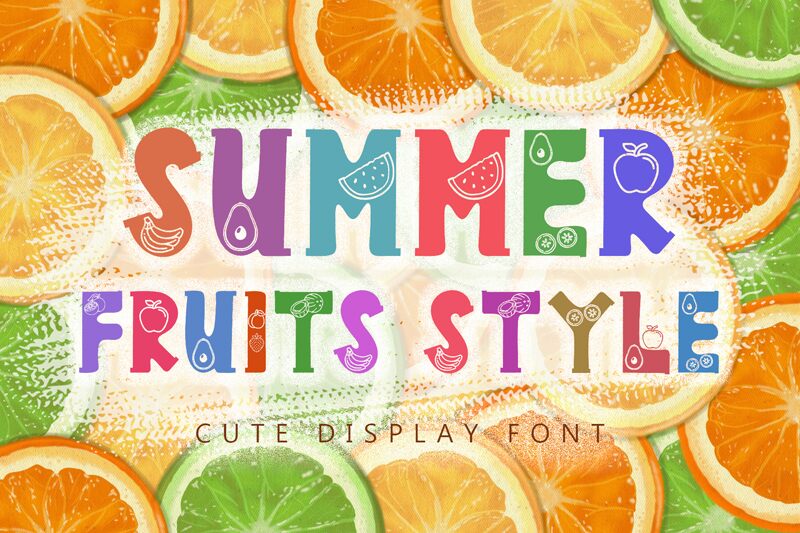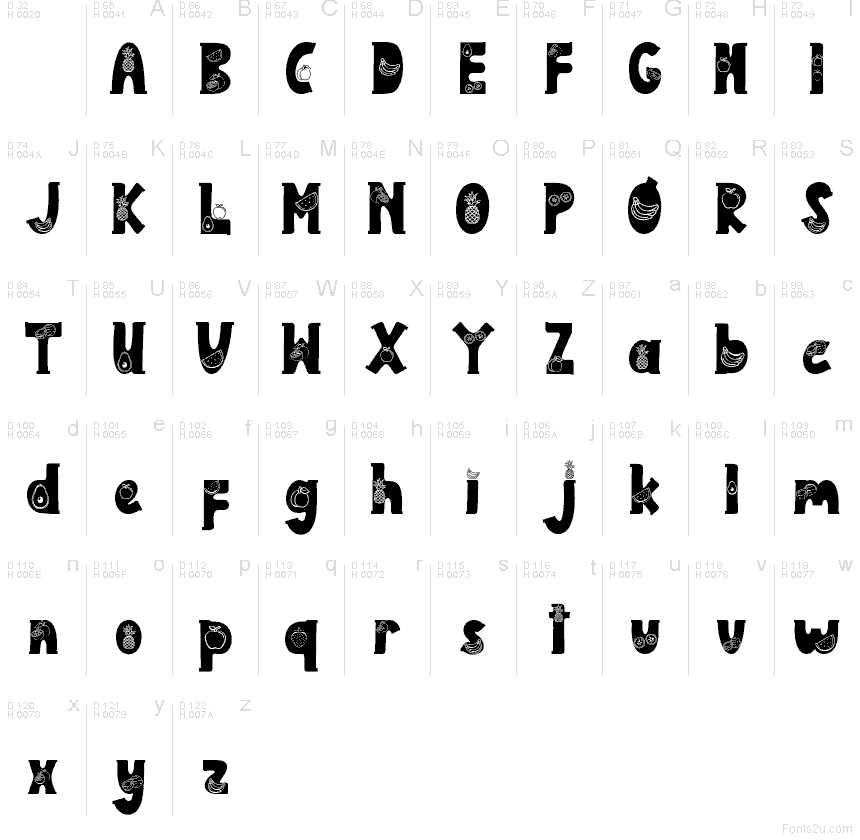
Summer Fruits Style Demo
Summer Fruits Style de Yoga Letter es una tipografía decorativa gratuita de estilo display, con formas redondeadas y un aire de cuento de hadas que integra dibujos de frutas. Las letras incluyen pequeños plátanos, rodajas de cítricos, trozos de sandía y el icono de una manzana, lo que le otorga un marcado tema de frutería sin perder su potente ritmo gráfico.
Esta fuente gratuita es perfecta para etiquetas de zumos, menús de cafeterías, invitaciones a fiestas veraniegas, cartelería de mercados y diseños para redes sociales que necesiten un título temático. Sus formas compactas y sus adornos frutales incorporados la hacen ideal para detalles en packaging, encabezados de pósteres y logos alegres vinculados a productos frescos o promociones de temporada.